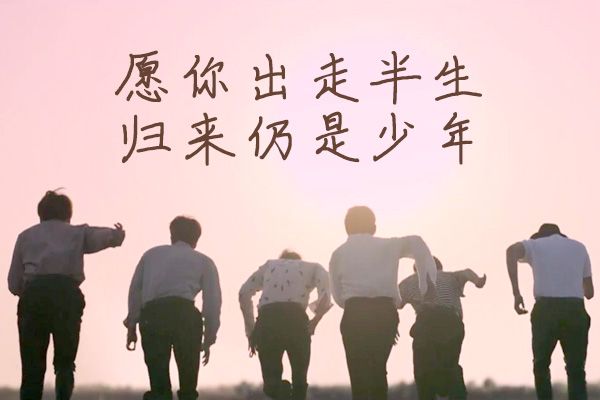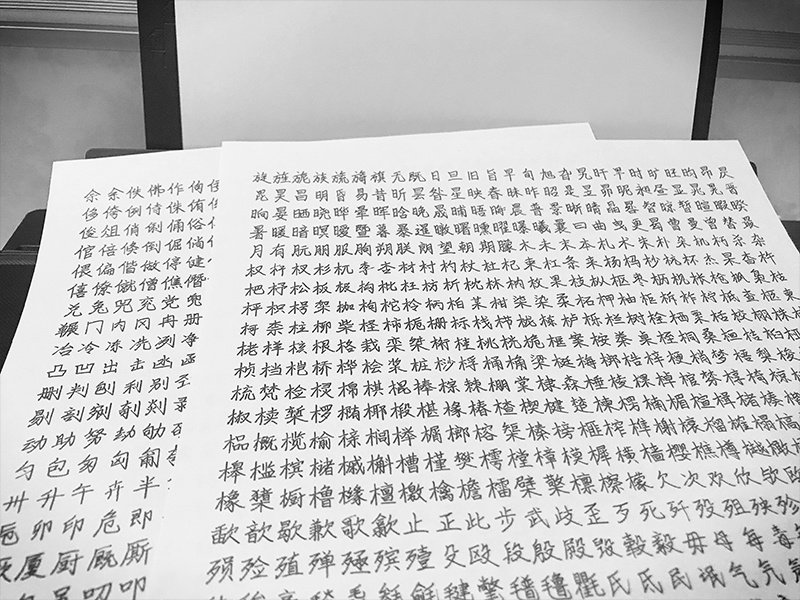
智勇手书体
智勇手书体是由站酷设计师Joker9创作的免费商用字体,包含基本汉字6763个。这款字体采用手写风格,给人们带来亲切自然的感觉,适用于各种设计场合,如slogan、banner、海报、商标等。使用智勇手书体,可以让您的设计更加生动活泼、富有个性。
智勇手书体效果预览
智勇手书体字体效果预览